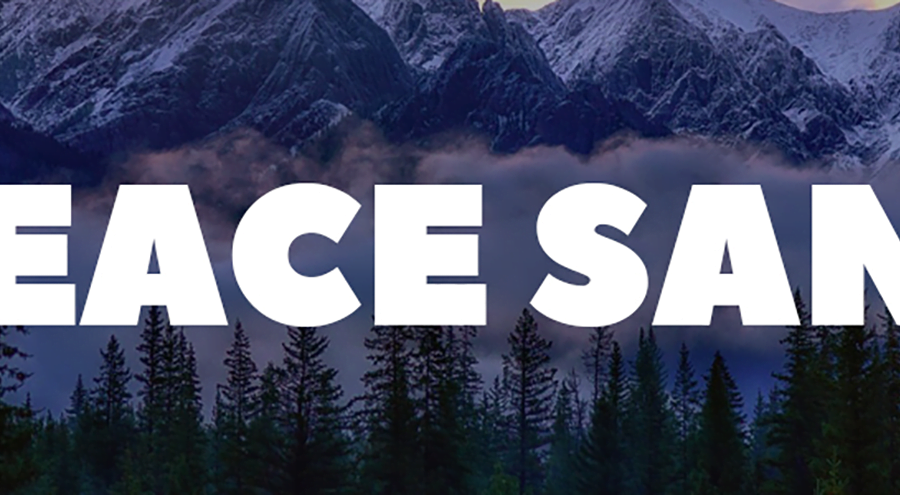
Découvrez sans plus attendre la typographie PEACE SANS. Améliorez vos créations graphiques grâce à cette police d’écriture bold réalisée par Sergey Ryadovy.
Celui-ci met à votre disposition une typo qui comprend des majuscules, des caractères numériques ainsi que la totalité des caractères multilingues tels que le cyrillic, latin, turque…